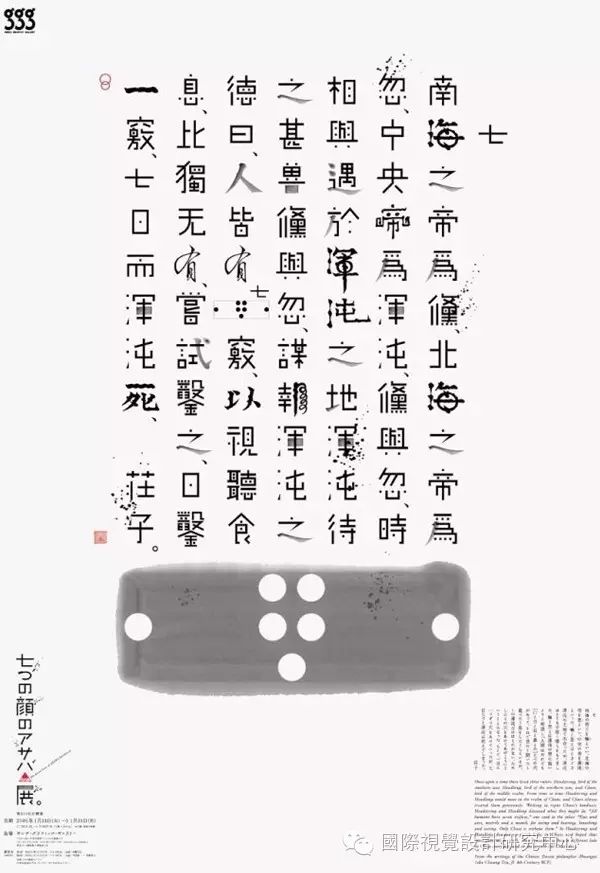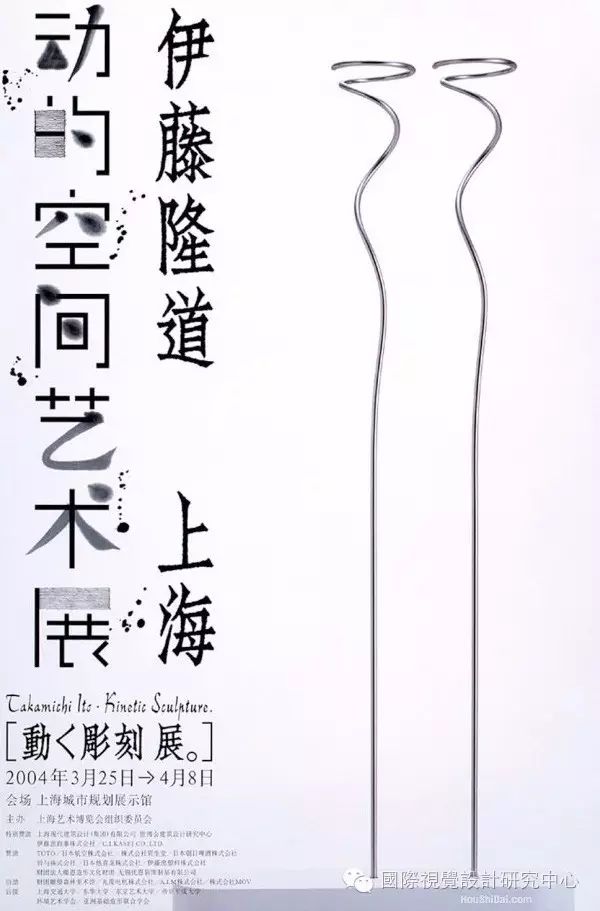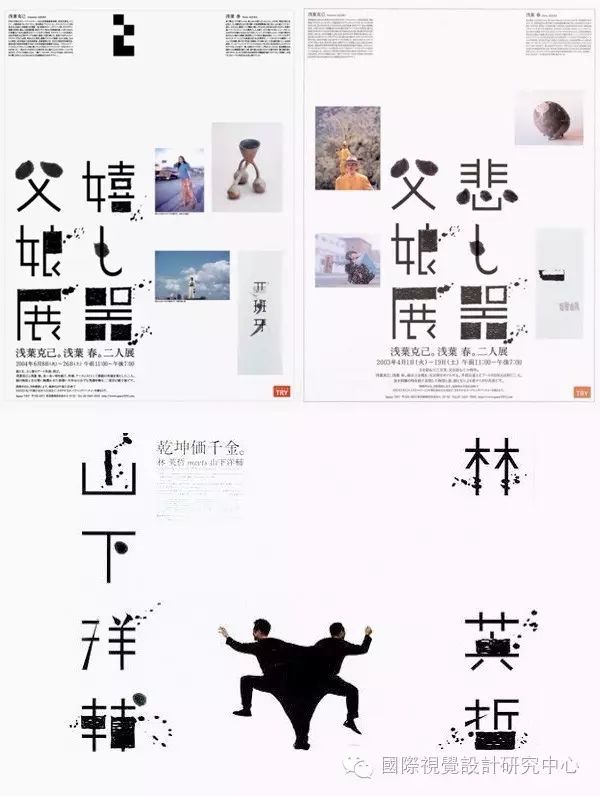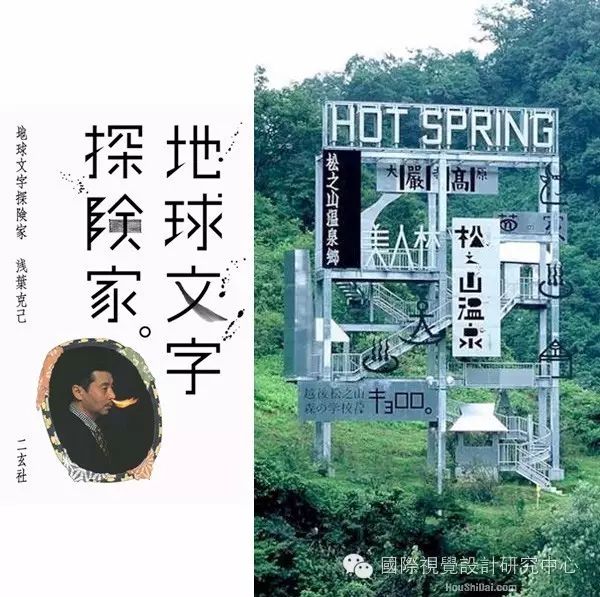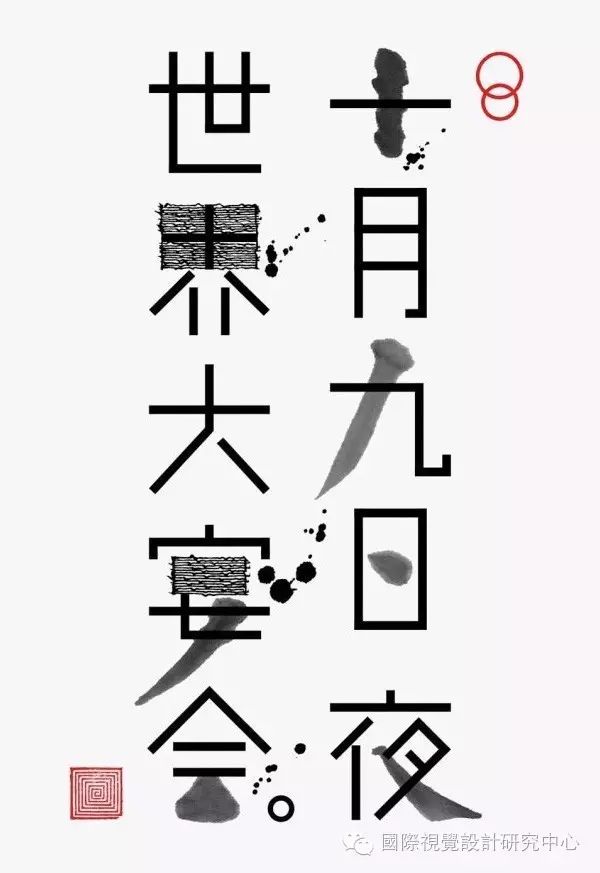
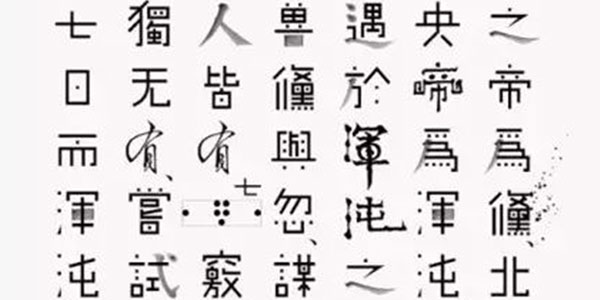
浅叶克己字体设计作品探析
二战结束后日本为了恢复经济开始发展现代设计,经过几十年努力便成为了世界设计大国,特别是日本平面设计的快速发展引起了世界各国的瞩目。日本能在短短的几十年间取得经济腾飞,成为世界强国,其产品畅销全世界,平面设计无疑充当了重要的角色。因此,日本平面设计快速发展的成功经验成为当今设计理论界研究的重要课题之一。日本广泛吸收欧美现代设计的长处,在跟随国际设计发展步伐的同时,更注重弘扬本民族的传统文化,这才使得日本平面设计在国际舞台上独具特色。正如日本设计家泉真也先生所说:“日本设计的第一特征是传统设计和现代设计的结合”,传统审美与现代时尚和谐地交织在一起,成为日本设计文化的奇观。我们不难发现凡是日本成功的一线设计师无一例外都饱含着对其民族深厚传统文化的热爱,保持着谨慎谦卑的态度,注重细节设计,崇尚自然风味,讲究大和文化的美学精神。在很多日本平面设计作品中都能感受到空灵禅意的宁静和悠远,在清雅、柔和的民族风格形式下,能清晰地感受到日本平面设计所传达的深刻精神内涵。正是这种文化精神的支撑,日本才能在国际平面设计领域中占有举足轻重的地位。日本的平面设计充分体现了传统文化和现代科技的有机结合,浅叶克己就是这样一位能够将传统和现代融会贯通的日本现代平面设计大师。
浅叶克己字体设计作品分析
在浅叶克己平面设计作品中对传统的继承,除了民族观念、民族审美、民族绘画外,他对民族文字特别是书法十分偏爱,文字不仅仅是传承文明的符号,在他那里还被升华为一种造型语言。浅叶克己说过:“文字有三个层面,一是书写在表面上的文字;二是语言学意义上的文字;还有就是激发人们的艺术想象力的文字。”浅叶克己正是用人类最直白的语言交流工具——文字来进行设计,用最简洁、最精炼、最有渗透力的文字形式,把内容准确鲜明地传达给受众,去激发人们的想象力。他运用了水墨技巧融入电脑字体的表现手法,来增强平面设计作品的文化底蕴;强化点、面在线性的字体设计中的构成作用,使作品更具现代感;并将笔画进行有规律的变化,使得文字创作更趋图形化。他通过以上这些方法的运用和反复探索,逐渐形成了浅叶克己式字体设计的符号化特征。
水墨结合电脑 增强文化品位
在浅叶克己的设计作品中,水墨技巧的运用不仅是形式还包括内容,使作品具有更深层次的人文含义。在东京银座ggg画廊展出的浅叶克己设计作品中,其中有一幅作品是对《庄子》的“混沌之死”进行的设计创作。浅叶克己利用古代诗歌传统的书写形式,运用水墨技巧融入电脑字体的创作手法,将文字的部分笔画用书法笔触来代替。特别是对文章中的“七”字进行水墨化的图形设计,在一块长方形的水墨上点了七个白点,这七个点代表了文章中提到的“七窍”,形成独具形式美感的书法艺术设计,给人以气韵生动之感。他用自己的理念和创作手法去解读庄子的思想,强调人的本性应是无为和自然的,让现代人感受到古人的智慧和道气。这幅作品给传统文化赋予了新的生命,是东方传统文化和现代设计完美结合的典范之作。
“动的空间艺术展”的宣传海报也是用了同样的表现手法,这幅海报构图简约,文字信息占了主要部分并位于画面的左边,其中“动的空间艺术展”这几个字用水墨手段结合电脑表现手法来进行字体设计,他把每一个字的部分笔画用书法形式来表现,设计后的文字让人耳目一新达到有效传达信息的作用。水墨的浓淡虚实再加上大面积的留白,使画面达到黑白灰层次分明的效果。电脑字体的规整和书法的洒脱形成对比,在动与静中取得了平衡。通过文字笔画浓与淡、黑与白、实与虚的对比,使画面富有生机和灵气。这种即传统又现代的设计手法,让人切实感受到艺术与设计的交融。浅叶克己还有一系列的平面设计作品是将电脑字体和水墨技巧相结合的,他作为一个日本人能这样重视汉字的书法传统,并运用得如此灵活自如,是很值得我们中国设计师学习和反思的。
运用线性构成 强化点面作用
点、线、面是最基本、最抽象的构成元素,它们能够组合成任何形态,是视觉艺术在平面构成中运用最多的概念要素。浅叶克己的字体设计在融入水墨表现手法的同时,也很注重画面中点、线、面构成元素的运用。汉字本身就是一种线性构成,浅叶克己在此基础上加入点和面元素,用构成学原理进行字体设计,将文字变成有点、线、面元素的组合图形,从而加强字体设计作品的现代感。
在浅叶克己和他女儿艺术作品父女展的宣传海报中,就是将“父女展”这几个关键字设计成有点、线、面的构成形式。首先,他将海报中的主要文字放在画面的左下方,左上方大面积留白,而右边只有几张图片,使文字信息成为观赏者的第一视点;再次,他将部分文字的笔画涂成黑色块,色块是带有笔触肌理的水墨效果,给人以透气的感觉,并形成有大小对比、浓淡虚实变化的面;最后,还在画面上扬扬洒洒留下多点墨迹。文字经他设计后,变成了运用线性构成、强化点面作用的构成创作,使文字起到不仅具有信息传达还能增强视觉美感的作用。
另外,在林英哲和山下洋辅二人展的宣传海报中,他同样将文字设计成有点、线、面元素构成的图形创作。这幅作品只采用黑白两色,画面极其简洁大方。画面中心的两个连体人充满了趣味,在吸引观众的同时,也形成一个黑色的大面,其两侧“英、哲、辅”三个字的部分笔画也被他涂成了黑色的块面,这样使得大小不同的块面构成了视觉上的黑白对比,其代表性的围绕在字体周围的多处墨点也起到了呼应黑色块面的作用。这幅作品是水墨表现手法和点、线、面构成元素的完美结合,使之成为浅叶克己海报中最具有生命力和感染力的作品之一。
探索笔画规律 字体化为图画
“地球文字探险家”的这张宣传海报,除了运用水墨和点、线、面元素外,浅叶克己还将文字笔画结构进行有规律的调整,使字体设计更具图画特征。首先,从整体上看这幅作品文字设计的框架性很强,每一个文字都像被放在一个方框里面,字体笔画的点、横、竖、撇、捺都压在这个不存在的方框边上,使文字笔画设计的规整性增强;再次,打破每个文字固定的笔画结构,寻找文字笔画内在的联系,每一个字都强调撇、捺的处理,特别是“地、球、探、险”这四个字偏旁的“提”笔画采用了同样的处理手法,由粗到细给人以犀利的感觉,而“险”字偏旁也设计成向上的形式,起到呼应前面“提”笔画的作用,让其文字设计具有一定的规律性;最后,再用书法笔画和墨点来打破规整,让文字设计创作即理性又不失感性,不乏设计感的同时又充满灵气。这样经其设计后的字体既有对比又有协调,达到创作风格上的整体统一。海报左下方的图片中浅叶克己的鼻子喷出火焰的“冒险”行为,与“探险家”这三个字形成呼应,使得作品充满趣味且更富表现力和感染力,让人过目难忘。
浅叶克己将文字笔画粗细、长短、疏密、大小进行有节奏韵律的创作排列,使文字变成具有设计美感的图形。在“十月九日夜,世界大宴会”这幅作品中,浅叶克己将电脑字体笔画进行统一的设计处理,使文字线条更加简洁,再加上具有浓淡变化的书法水墨笔画,配合左下角的印章,使这幅作品变成一幅地道的书法作品。他用了四条竖的辅助线,让左右走向的电脑笔画没有超出边界,他还将电脑字体中弯曲的笔画变成棱角分明的转折笔画,增强了文字的横平竖直感,特别是“月、九、夜、大、宴”这几个字的转折处,轻盈的线条加上硬朗的转折,使文字在阴柔中又具有阳刚之美。他还特别注重撇的笔画处理,特别是水墨的撇笔画都进行了规律性的强调处理,增强了文字设计创作上的秩序美。
结语
吸取传统文化的精髓是日本平面设计不断进步的基石,日本平面设计将传统文化赋予现代设计以新的活力,向世界显示了其无与伦比的魅力。浅叶克己作为日本第三代优秀平面设计师,以字体设计独树一帜。他充分挖掘文字的线性魅力,来表现字体设计的图形意味,并加入他个性化的表现手法,使得其设计作品具有丰富的内涵和意境,作品中每一处的精心设计,都是他在表达自己的创作主张和设计理念。同时,由于字体设计的局限性,只能在表现手法、构成元素以及笔画结构上来做文章,使文字不仅具有传达信息的作用,更重要的是把文字变成图画来设计创作。浅叶克己先生在进行字体设计创作时,使用水墨技巧融入电脑字体的表现手法,营造出一种东方文字特有的虚实关系,从而表达出设计者清雅和悠远的意境;用现代平面构成的设计法则来进行字体设计创作,强化点、面在线性的字体设计中的构成作用;并将字体笔画进行有规律的变化,将文字创作图形符号化,使字体设计作品具有个人独特的表现形式和深刻的文化内涵。浅叶克己的设计作品在传统与现代、设计与艺术、字体与图形中找到了完美的契合点,这正是他设计作品之所以获得成功的关键所在。